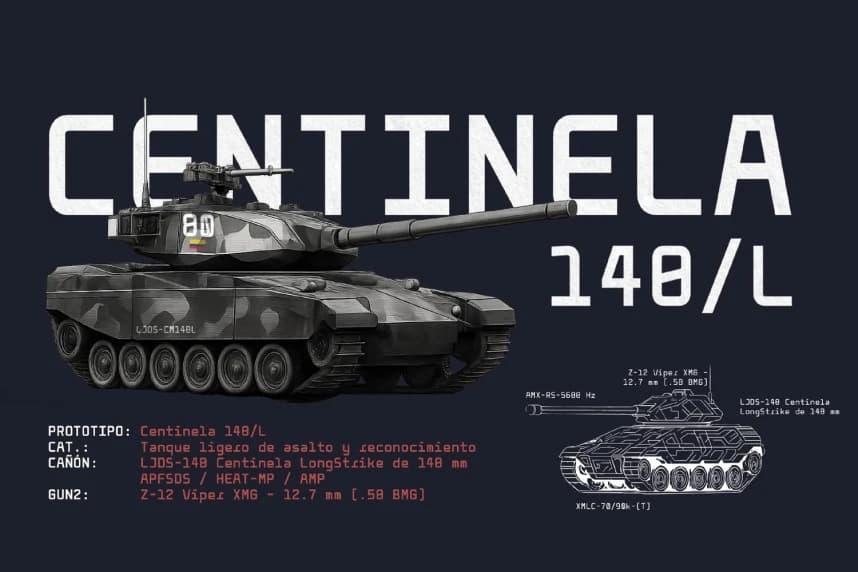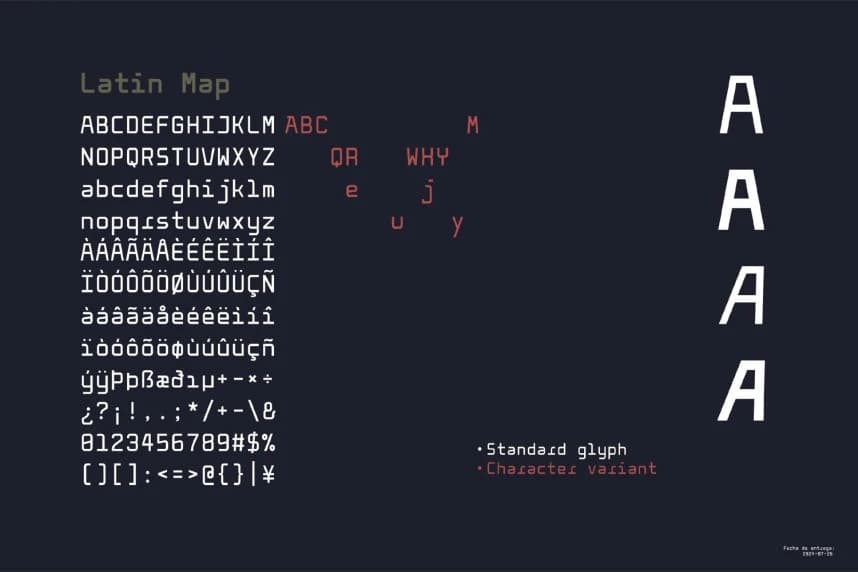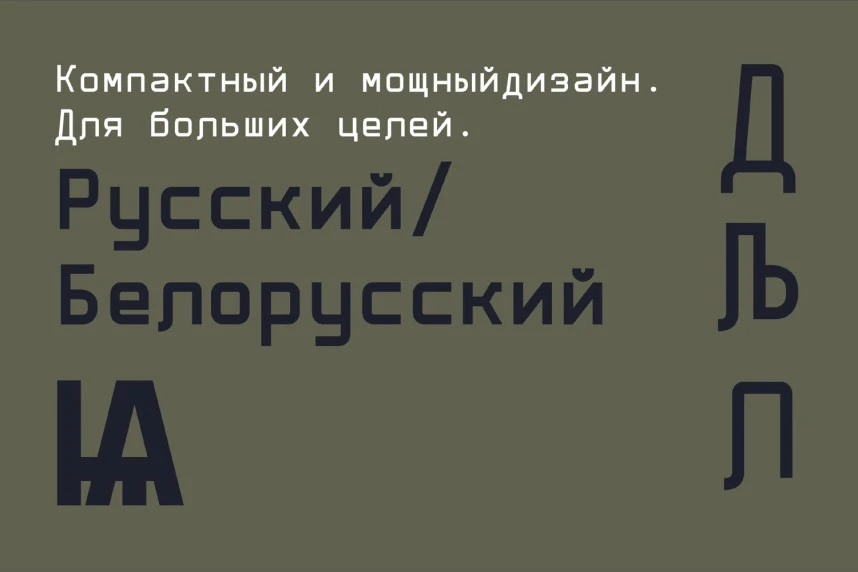
Centinela Mono Font
Centinela Mono Font, programlama konsolları için oluşturulmuş bir monospace fontudur. Basit ve modern bir stile sahiptir ve herhangi bir programlama veya kodlama ortamına mükemmel şekilde uyum sağlar. Sublime, Python gibi platformlarda veya herhangi bir metin motorunda çalışmak için mükemmeldir.
Centinela Mono Font, programlama konsolları için oluşturulmuş bir monospace yazı tipidir. Basit ve modern bir stile sahiptir ve herhangi bir programlama veya kodlama ortamına mükemmel uyum sağlar. Sublime, Python gibi platformlarla çalışmak için mükemmeldir ya da herhangi bir metin motoruyla çalışmaya da uygundur.